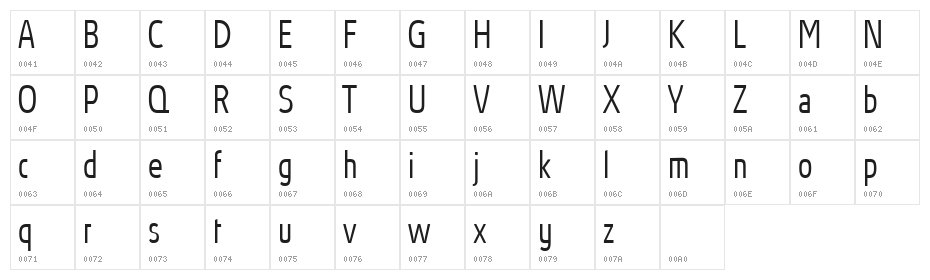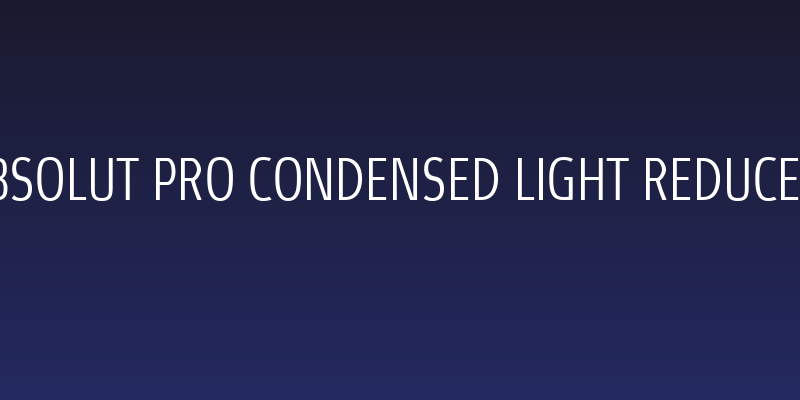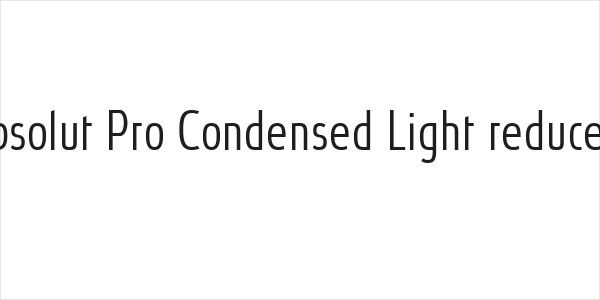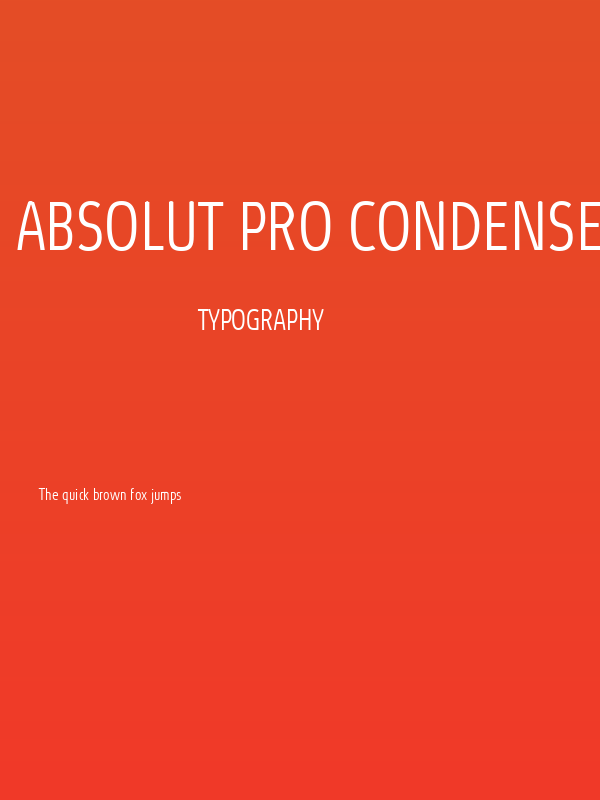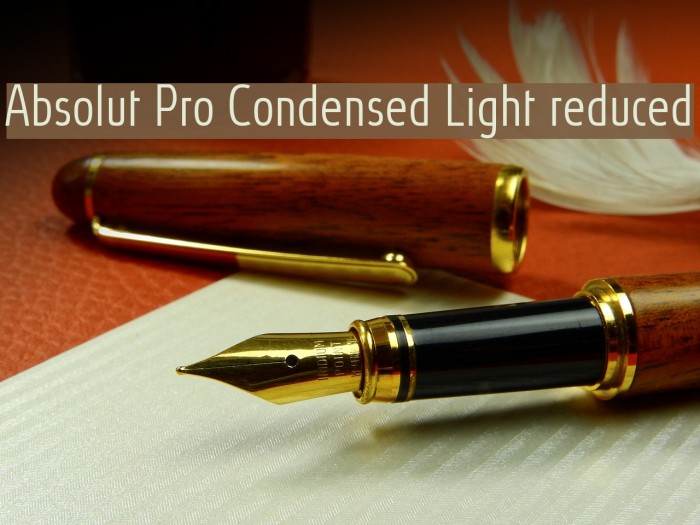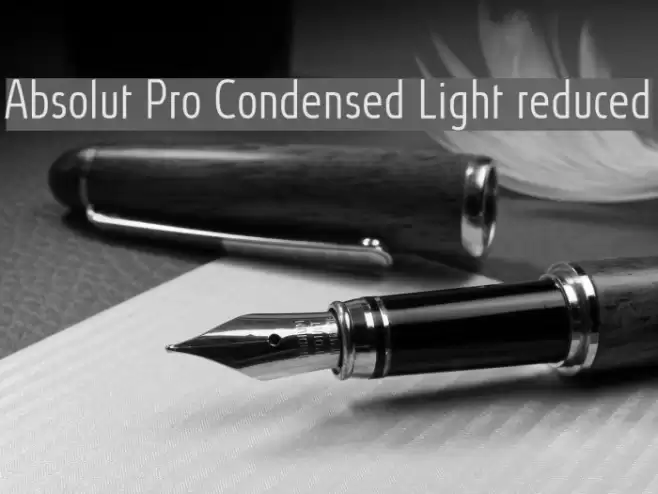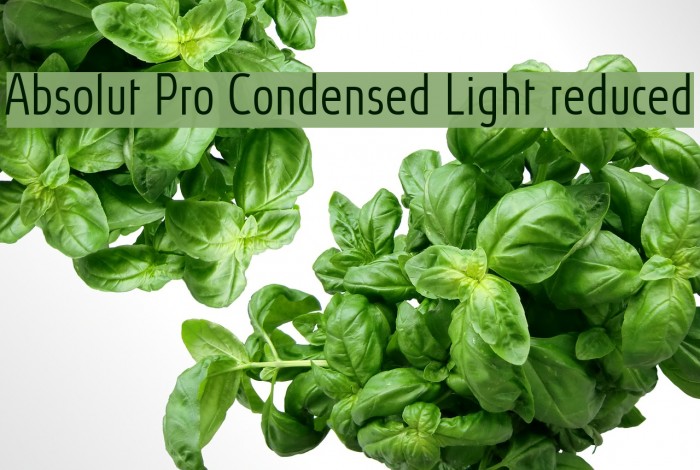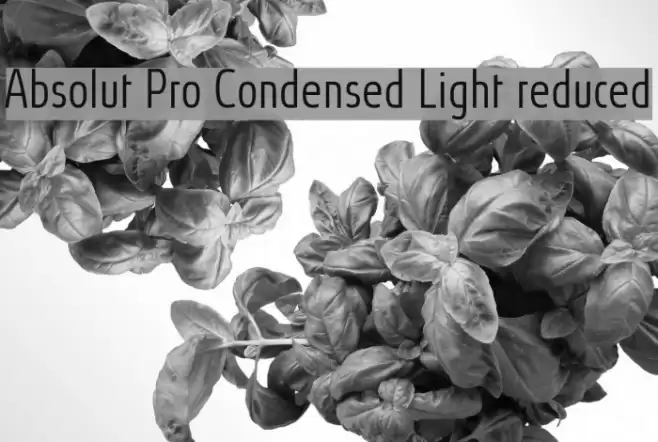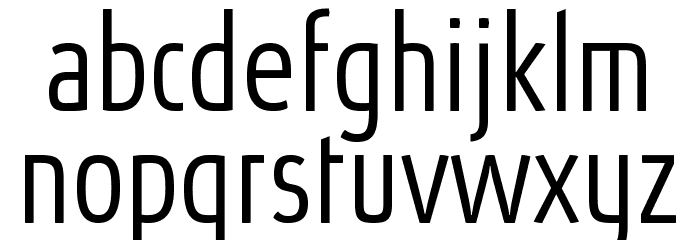
Absolut Pro Condensed Light reduced Font
Fonts by Ingo Zimmermann - www.ingofonts.com
| Anwendungsfall | Headlines, Body text, Logos |
| Vorgeschlagene Projekte | Ideal for branding, advertising, editorial design, and digital interfaces where a modern and clean look is desired. |